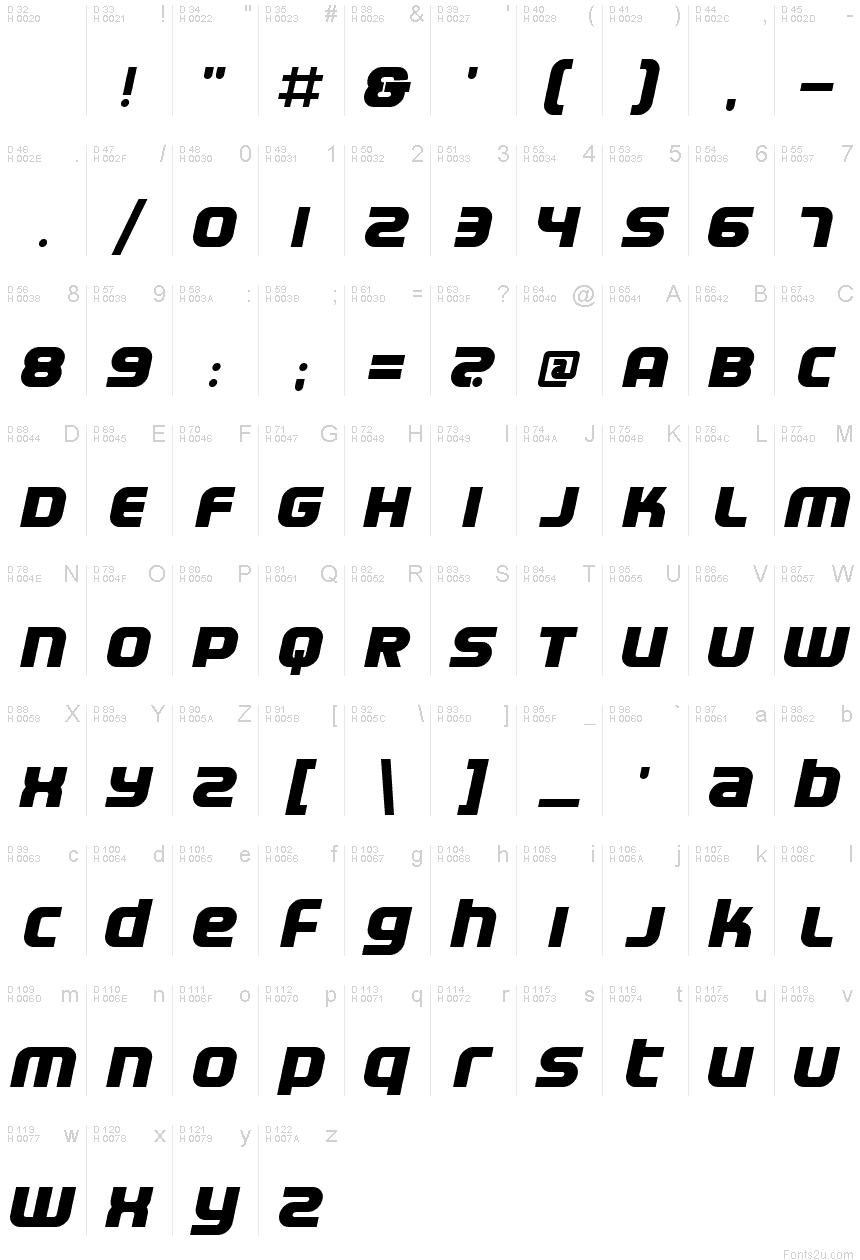
Electrofied BoldItalic
Krój Electrofied Bold Italic od dustBUST Fonts to nowoczesny, darmowy font typu display, który natychmiast przyciąga wzrok dynamiką i energią. Grube, zaokrąglone pociągnięcia i wyraźne pochylenie w przód sprawiają, że każde słowo wygląda, jakby pędziło po cyfrowym torze, a miękkie krawędzie nadają mu gładki, nowoczesny charakter bez zbędnej agresji. Ta pogrubiona kursywa z rodziny Electrofied wyróżnia się kompaktowym, opływowym profilem, przypominającym w dotyku gładki plastik podświetlony diodami LED.
Electrofied Bold Italic świetnie sprawdzi się w efektownych nagłówkach dla zespołów e-sportowych, startupów technologicznych, na plakatach eventów EDM, okładkach sci-fi, nakładkach do streamingu czy futurystycznych opakowaniach produktów. Ten darmowy font najlepiej prezentuje się w dużych rozmiarach, gdzie jego ciasny rytm i nachylone formy mogą w pełni wybrzmieć; zastosuj odrobinę większe światło między literami, aby uzyskać maksymalną czytelność. W tekście głównym połącz go z prostym, dyskretnym bezszeryfowym krojem geometrycznym, aby Electrofied mógł grać główną rolę.